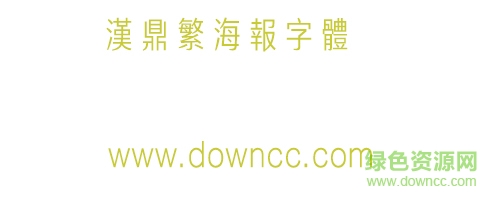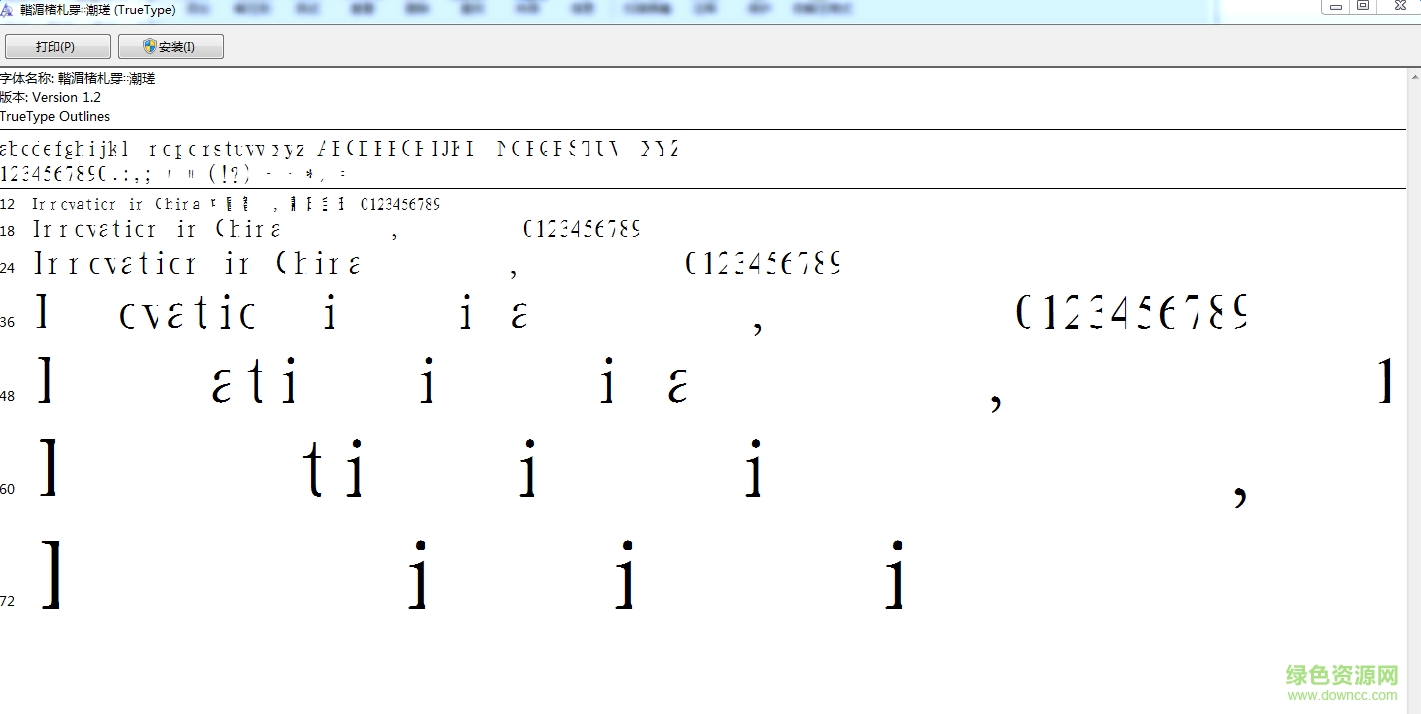
漢鼎繁海報(bào)字體是一款漢鼎海報(bào)類繁體字體軟件,繁體字給人非常古老的感覺(jué),深受廣大書法家的喜愛(ài),適用于海報(bào)等字體需求,還有更多好看字體盡情期待,歡迎到綠色資源網(wǎng)下載體驗(yàn)!
用于海報(bào)設(shè)計(jì)方面的字體,字體工整美觀,可用于出版印刷字體、廣告設(shè)計(jì)字體、網(wǎng)頁(yè)設(shè)計(jì)字體、包裝設(shè)計(jì)字體、 屏幕顯示字體
漢鼎繁海報(bào)是一款海報(bào)類繁體字體,字體效果比較繁瑣,喜歡繁體字的朋友可以下載使用看看效果如何。